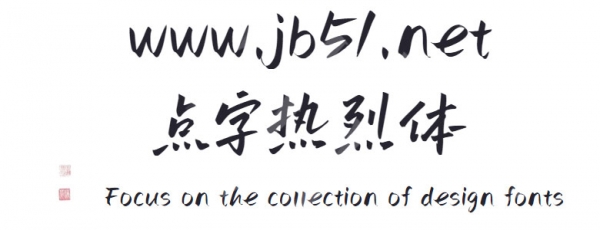
點(diǎn)字熱烈體是由點(diǎn)字庫(kù)推出的藝術(shù)字體,字體字形結(jié)構(gòu)舒展,筆畫(huà)設(shè)計(jì)自然優(yōu)美,多字組合富有手寫(xiě)節(jié)奏感,適合應(yīng)用于藝術(shù)設(shè)計(jì)、各類廣告和產(chǎn)品包裝設(shè)計(jì)等領(lǐng)域。
這是一款輕松隨性的創(chuàng)意手寫(xiě)字體,其字形結(jié)構(gòu)舒展,筆畫(huà)設(shè)計(jì)自然優(yōu)美,多字組合富有手寫(xiě)節(jié)奏感。適用于文藝類的書(shū)刊、品牌廣告和產(chǎn)品包裝設(shè)計(jì)。